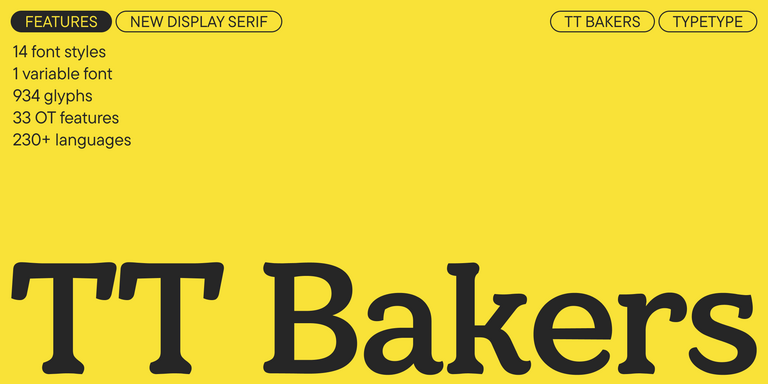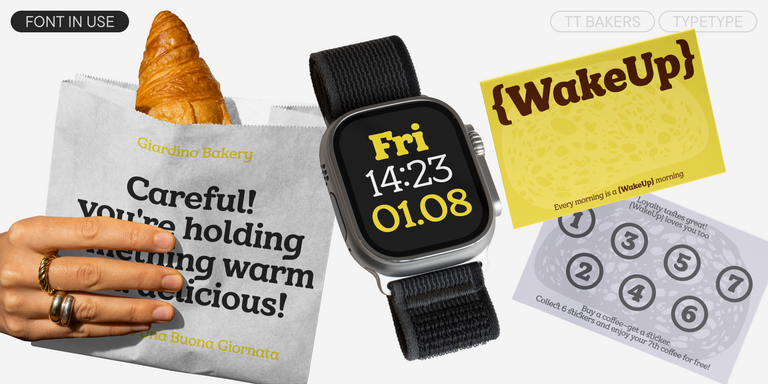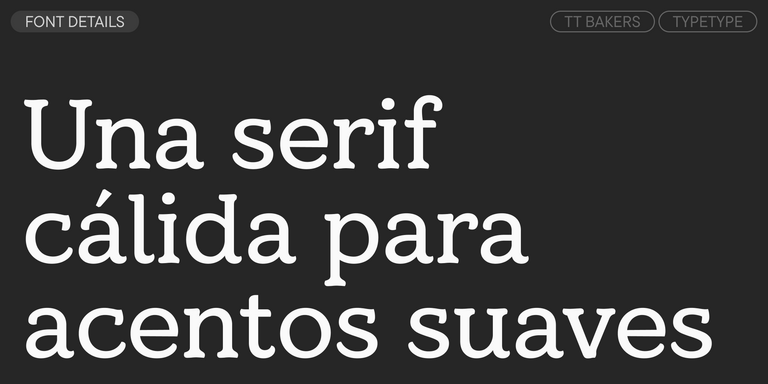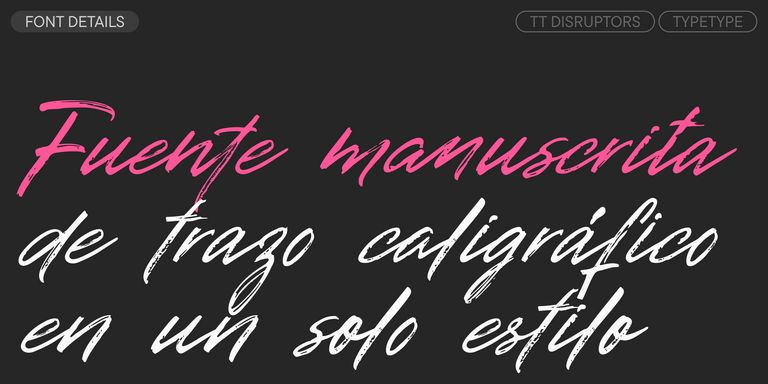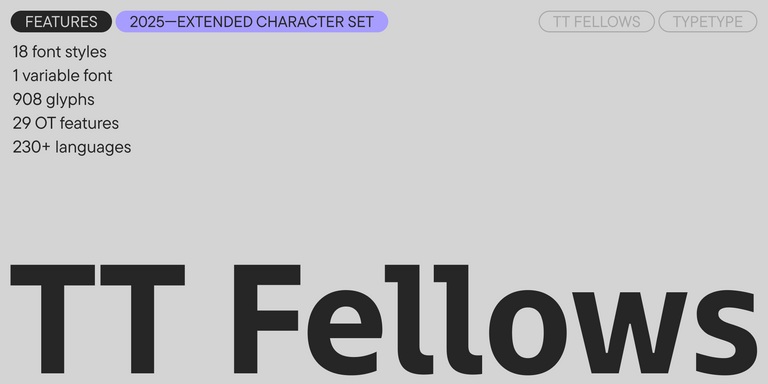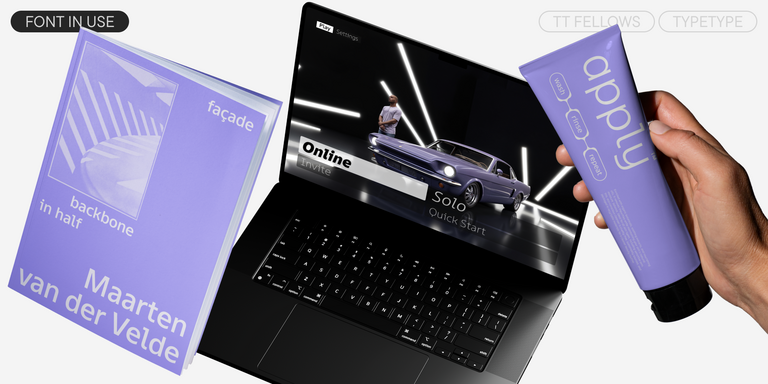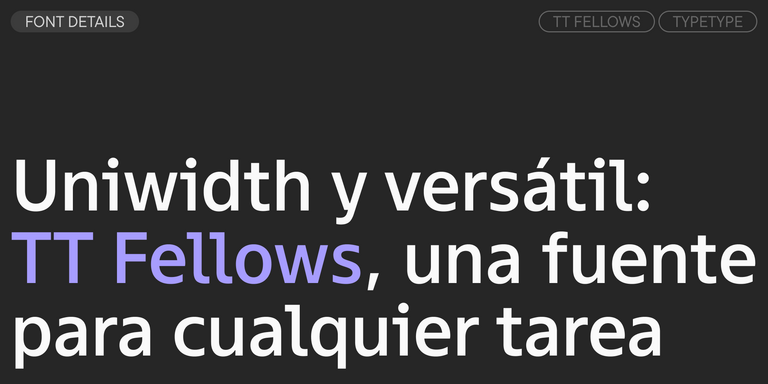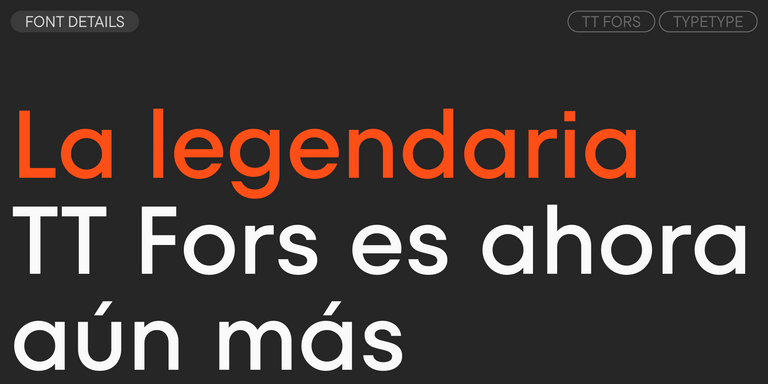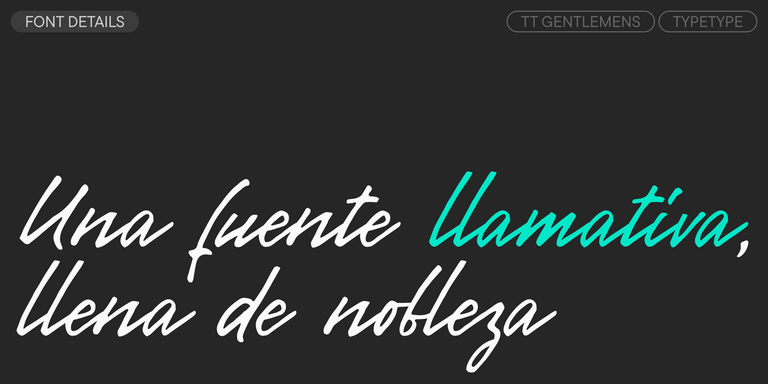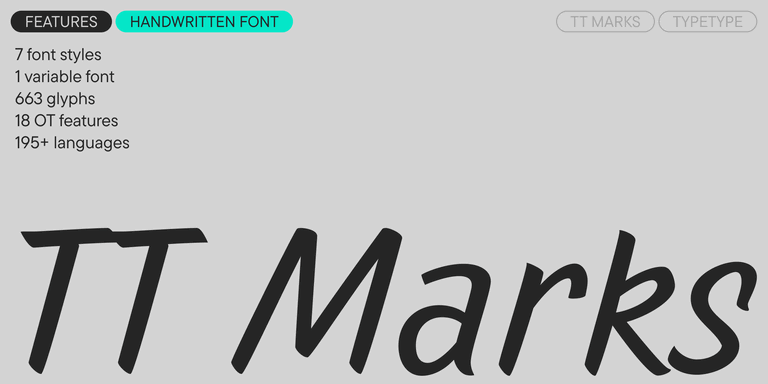
Adobe Illustrator Schriftarten
Die Kollektionen von TypeType umfassen stilvolle, benutzerfreundliche Schriftfamilien, die speziell für kreative Software entwickelt wurden. Unsere Adobe Illustrator-Schriften lassen Ihre Designs hervorstechen — ob bei der Gestaltung von Logo-Buchstaben, Plakat-Symbolen oder zeitgenössischer Typografie. Sie finden mühelos die perfekte Schriftart für jedes Projekt, und die Arbeit mit ihnen in Illustrator optimiert Ihren kreativen Workflow.
TT Commons™ Pro ist eine vollständig neu gestaltete Version der etablierten klassischen Schriftfamilie TT Commons.
TT Hoves Pro ist eine vielseitige Sans Serif mit wiedererkennbarer Geometrie.
Wir erweitern weiterhin die Linie des wichtigsten Bestsellers unseres Studios: TT Norms® Pro!
TT Livret ist eine elegante, moderne und funktionale Serifenschrift.
TT Polihaus ist eine experimentelle Grotesk, die auf den ersten Blick konventionell wirkt, sich dann jedoch zunehmend in einzelne Elemente auflöst und schließlich eine stencilartige Struktur annimmt.
TT Nooks Serif ist eine Akzidenz-Antiqua mit klassizistischem Charakter und einem leichten Zug ins Egozentrische. Ihr Charakter ist scharf und gefestigt, zugleich elegant und stattlich.
Die Schrift TT Chocolates besteht aus 14 Fonts: 7 Strichstärken und 7 Obliques. Sie bietet erweiterte Sprachunterstützung und nützliche Features.
TT Nooks Script besitzt eine eigenständige Zeichnung, für die es kaum direkte Vergleichspunkte gibt.
TT Qurdisma ist eine schmale, kompakte dekorative Schrift, die an eine eigenwillige Pflanze erinnert. Ihre geschwungenen, fließenden Konturen bilden ein pflanzliches Ornament.
TT Neoris ist eine elegante Neo-Grotesk mit unbegrenztem Potenzial — eine Schrift, die alle modernen Anforderungen und Wünsche der Nutzer vereint.
TT Supermolot Neue ist eine neu gestaltete, erweiterte und deutlich verbesserte Reinkarnation der beliebten Schriftfamilie.
TT Norms® Pro ist eine typografische Legende, die von weltbekannten Marken geschätzt wird. Entwickelt durch mehrere Iterationen, hat sie MyFonts erobert und typografische Vielseitigkeit neu definiert. Ein Design-Arbeitspferd, das sich von einem bescheidenen Werkzeug in einen unverzichtbaren kreativen Begleiter verwandelt.
TT Commons™ Pro ist das typografische Kraftpaket des Studios. Eine Schriftart, die so vielseitig ist, dass sie sich einer Kategorisierung entzieht und Stil und Funktion nahtlos verbindet. Für Designer, die eine universelle Grundlage suchen, die jedes Projekt aufwertet, ist dies die endgültige Wahl.
TT Hoves Pro ist eine skandinavische serifenlose Schrift, die minimalistische Eleganz versprüht. Sie ist die Geheimwaffe eines Designers, der komplexe Herausforderungen mit müheloser Präzision in visuelle Poesie umwandelt, und dabei gleichzeitig dezent und unverwechselbar.
TT Supermolot Neue verändert die visuelle Kommunikation grundlegend! Eine fortschrittliche, modulare serifenlose Schrift, die den Puls der technologischen Innovation einfängt und eine elektrisierende Vision für alles von immersiven Spieloberflächen bis hin zu kühnen visuellen Erzählungen bietet.
TT Firs Neue ist eine ausgewogene serifenlose Schrift, die von der skandinavischen Designphilosophie geprägt ist. Elegant und vielseitig, poliert durch zwei bewusste Überarbeitungen, um typografische Perfektion zu erreichen.
TT Rounds Neue ist eine weiche und freundliche Schrift, die es versteht, anders zu sein. In leichteren Schriftschnitten wirkt sie minimalistisch und neutral. In den fetten Schriftschnitten bläht sie sich auf und erreicht maximale Rundheit, die kindlichen Charme ausstrahlt.
TT Fors ist ein Schweizer Taschenmesser der Typografie. Diese geometrische serifenlose Schrift ist durch ihre klaren, raffinierten Proportionen vielseitig einsetzbar. Sie kann zur Definition von Schnittstellen oder zur Gestaltung von visuellen Akzenten verwendet werden.
TT Ramillas ist eine stilvolle und moderne Serifenschrift, die Design zu einer Kunstform erhebt. Sie zeichnet sich durch ihre einzigartigen dekorativen Stile und Initialen mit floralem Ornament aus und schafft visuelle Erlebnisse, die wirklich einmalig sind. Die mit dem Modern Cyrillic Award ausgezeichnete Schrift, die bereits über 3000 Websites weltweit ziert, definiert typografische Raffinesse neu.
TT Marks bietet eine Schreibschrift mit dynamischem Rhythmus, emotionalem Charakter und nostalgischem Flair, inspiriert von der klassischen amerikanischen Kunst der Schildermalerei. Dieses Handwerk, bei dem erfahrene Künstler Geschäftsschilder mit Pinseln und großer Präzision von Hand bemalten, erlebt heute eine wohlverdiente Renaissance in der Designwelt.
TT Fors ist eine moderne geometrische Sans Serif mit Zeichen und Formen, die sich in ihrer Breite kontrastreich unterscheiden.
TT Fellows ist eine humanistische Sans Serif mit mechanischer Anmutung.